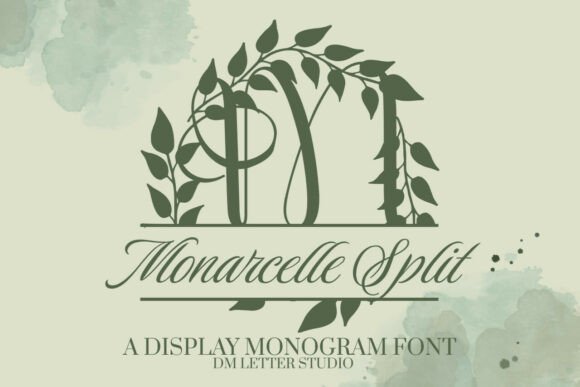
Monarcelle Split Monogram
Monarcelle Split Monogramのような高品質の素材をお探しの場合、このプレミアムパッケージはクリエイティブなプロジェクトに素晴らしい選択です。
精密に作られたMonarcelle Split Monogramは、クリーンなベクター、滑らかなタイポグラフィ、そして安心のための商用ライセンスを提供します。
POD(オンデマンド印刷)製品、結婚式の招待状、またはソーシャルメディアのグラフィックを作成している場合でも、Monarcelle Split Monogramは理想的です。